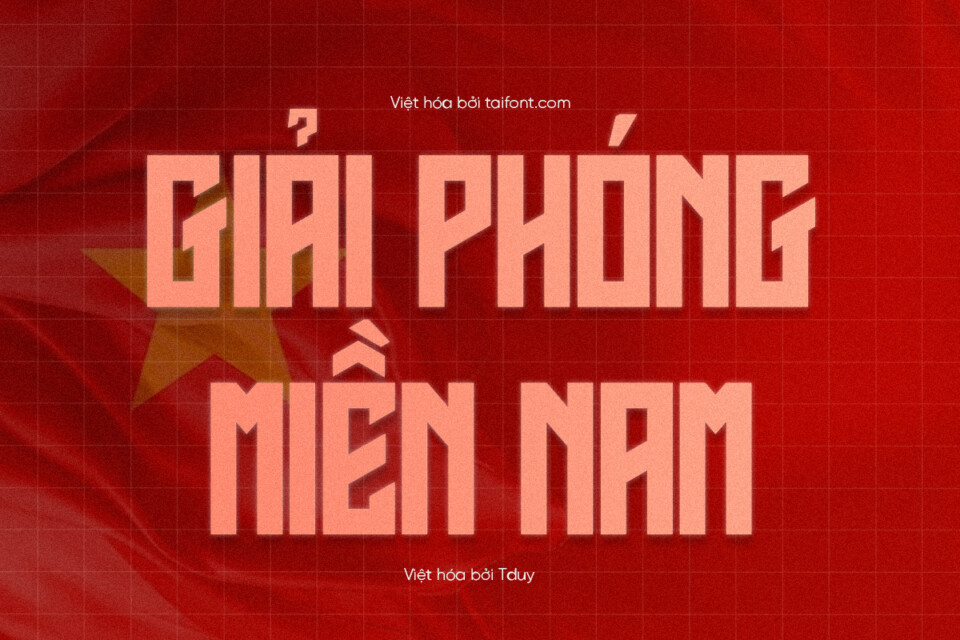
Font DL Calvera Việt Hóa – Font Trang Trí Mạnh Mẽ Cho Thiết Kế Lễ 30/4Tìm Hiểu Về Font DL Calvera Việt Hóa – Font Trang Trí Mạnh Mẽ Cho Thiết Kế Lễ 30/4Khi thiết kế các ấn phẩm truyền thông cho ngày giải phóng miền Nam, việc lựa chọn một Font Miễn Phí phù hợp là vô cùng quan trọng. Font DL Calvera Việt Hóa – Font Trang Trí Mạnh Mẽ Cho Thiết Kế Lễ 30/4 chính là giải pháp hoàn hảo giúp các bạn học sinh và thầy cô tạo nên những layout ấn tượng. Đây là bộ font chữ sở hữu các đường nét dày dặn, góc cạnh và mang tinh thần kiên cường. Kiểu dáng này cực kỳ thích hợp để làm nổi bật tinh thần hào hùng của ngày đại lễ lịch sử.Ứng Dụng Thực Tế Trong Nhà TrườngBộ font trang trí này phát huy tối đa hiệu quả khi ứng dụng vào các slide bài giảng lịch sử, banner chào mừng hoặc áp phích tuyên truyền của đoàn trường. Nhờ cấu trúc hình khối vững chãi, font giúp thông điệp truyền tải trở nên trang trọng và dễ dàng thu hút người xem từ ánh nhìn đầu tiên.Ưu Điểm Của Bộ Font Chữ Trang Trí 30/4Tối Ưu Tiếng Việt Hoàn HảoĐiểm cộng lớn nhất của bộ font này là đã được chỉn chu hóa toàn bộ hệ thống dấu tiếng Việt. Người dùng sẽ không còn gặp lỗi hiển thị hay bị mất nét khi gõ các ký tự đặc trưng, giúp quá trình thiết kế diễn ra nhanh chóng.Phong Cách Hiện Đại Và Đa DạngDù mang nét cổ điển của những biểu ngữ truyền thống, font vẫn giữ được tinh thần hiện đại, dễ phối hợp với nhiều màu sắc rực rỡ như đỏ và vàng trên các phông nền sân khấu.Kết Luận Và Tải XuốngSở hữu ngay Font DL Calvera Việt Hóa – Font Trang Trí Mạnh Mẽ Cho Thiết Kế Lễ 30/4 để nâng tầm các tác phẩm sáng tạo của bạn. Hãy truy cập Font Miễn Phí, Font Việt Hóa, Font DL Calvera Việt Hóa – Font Trang Trí Mạnh Mẽ Cho Thiết Kế Lễ 30/4 để tải về công cụ tuyệt vời này hoàn toàn miễn phí và bắt đầu thiết kế ngay hôm nay.
Font DL Calvera Việt Hóa – Font Trang Trí Mạnh Mẽ Cho Thiết Kế Lễ 30/4